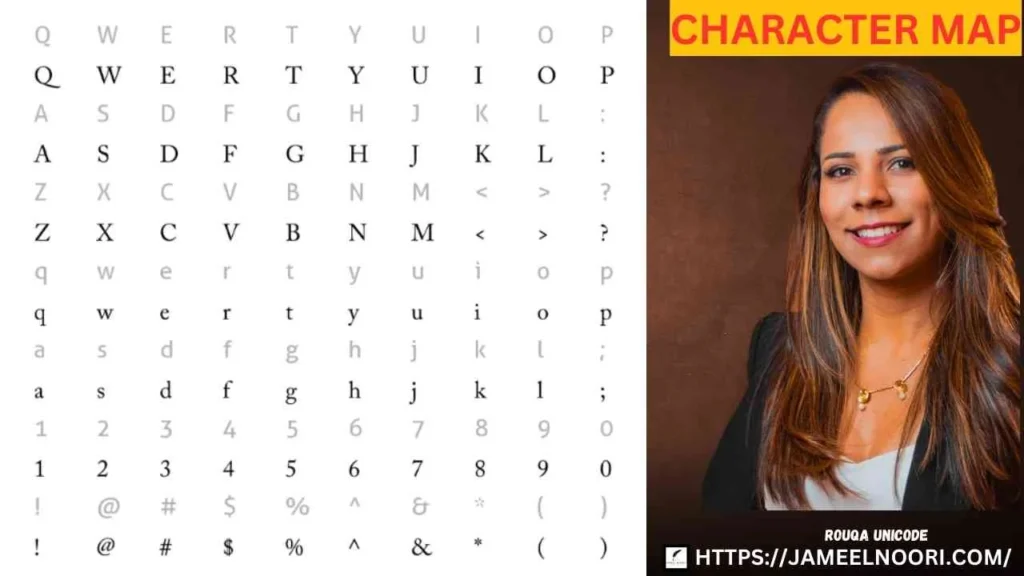
Agar aap Urdu likhne ya designing ke shaukeen hain to Download Urdu Font Rouqa Unicode aapke liye ek zabardast choice hai. Ye font ek TrueType Font (TTF) format me available hai jo Windows, Mac aur Android devices pe asaani se chal jata hai. Pakistan me students, designers aur bloggers isko use karte hain apne Urdu projects ke liye.
Features of Download Urdu Font Rouqa Unicode
Download Urdu Font Rouqa Unicode me kuch khaas features hain jo isko unique banate hain:
- Stylish aur readable Urdu design
- Unicode supported (har jagah compatible)
Benefits of Using Download Urdu Font Rouqa Unicode in Pakistan
Pakistan ke designers aur writers ke liye Download Urdu Font Rouqa Unicode bohot faida mand hai. Kuch main benefits ye hain:
- ✅ Urdu blogs aur websites me professional look
- ✅ Graphic designing (banners, logos, flyers) ke liye stylish text
- ✅ Educational use – students easily Urdu projects likh sakte hain
Why Choose Download Urdu Font Rouqa Unicode?
Market me hundreds of Urdu fonts available hain, lekin Download Urdu Font Rouqa Unicode ko prefer karne ki wajah ye hai ke iska design simple aur elegant hai. Ye beginners aur professionals dono ke liye best hai.
Key Reasons:
- Smooth rendering on all devices
- User-friendly & widely used in Pakistan (Lahore, Karachi, Islamabad)
Agar aap Urdu me stylish aur readable writing karna chahte hain to Download Urdu Font Rouqa Unicode aapke liye ek best option hai. Ye free, easy-to-install aur widely used font hai jo Pakistan me students, designers aur bloggers ke liye perfect choice ban gaya hai.